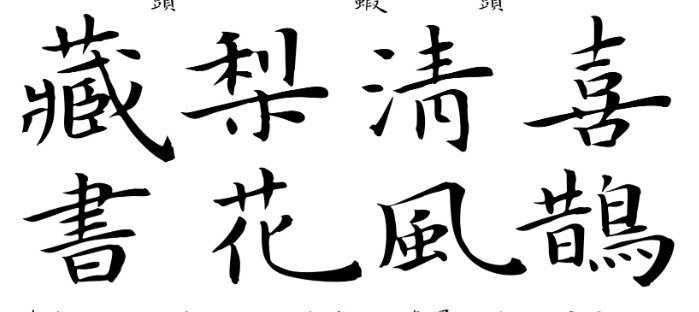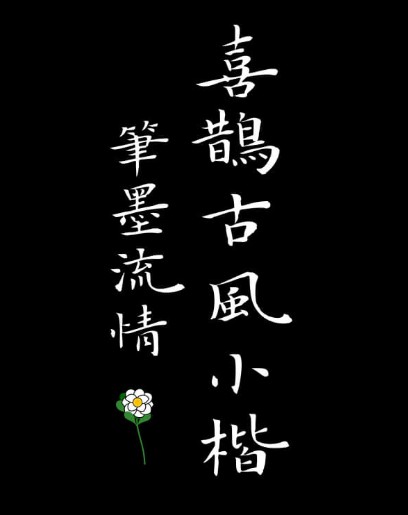
喜鹊古风小楷
字体介绍:书写者取法自王羲之《黄庭经》与王宠手书,有魏晋时代大王舒朗宽扁间架结构,亦糅合了王宠明清时代书卷气之点画特征,给人感觉干净如朗月皎洁,恬静如迎面清风。是一款味道十足的古风小楷体。
适用于:各种中国风的标题或正文场景,如国潮国漫、文创汉服、古典书籍、影视与传统文化相关等场景中。